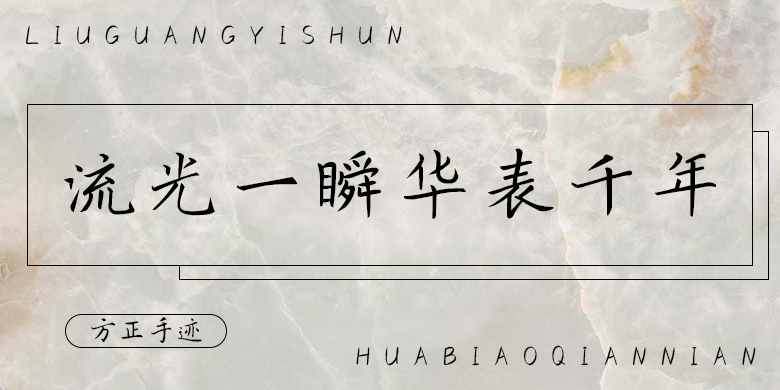
方正手迹-流光一瞬华表千年
字体品牌: 方正手迹 设计师:王航 字体分类:常规书写·硬笔 字体属性:精品字 字符集:简繁扩展(GBK) 发布时间: 2021
流光一瞬华表千年是一款传统书法风格楷书字体,字体风格整体脱胎于唐楷,可以看出欧阳询,褚遂良,柳公权的影子,结构严谨又不拘一格,大小错落又自然,风格独特,印象深刻。适用于广告设计、名片设计、包装印刷、产品设计等领域。